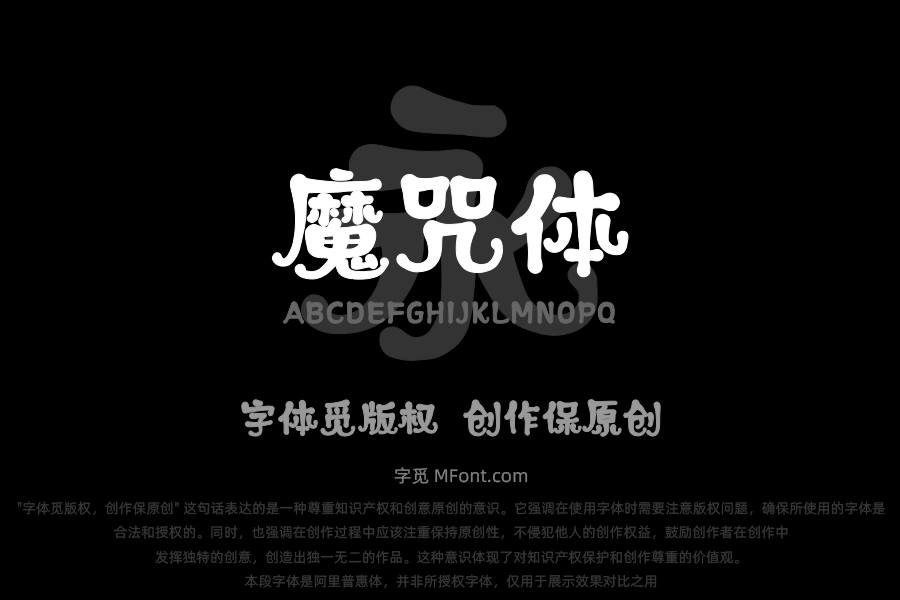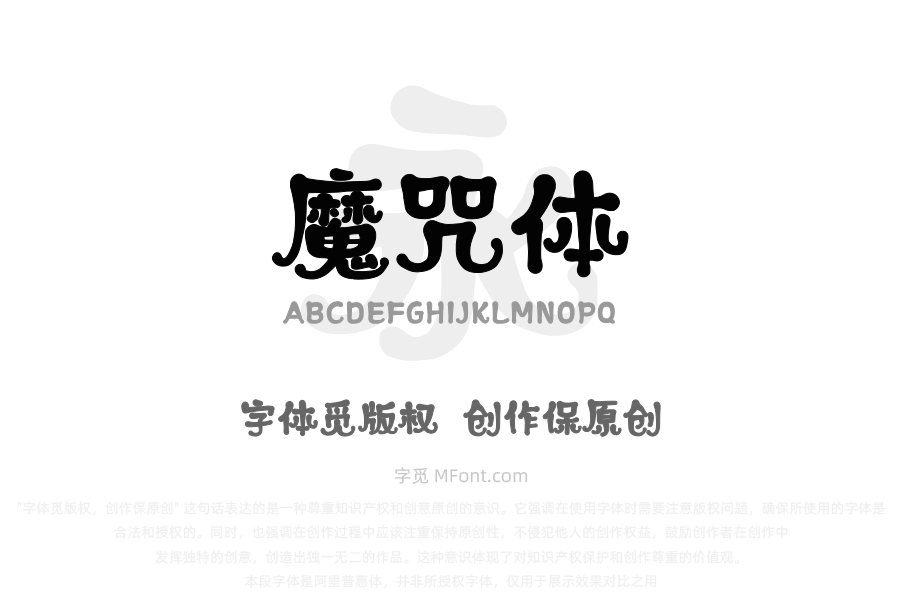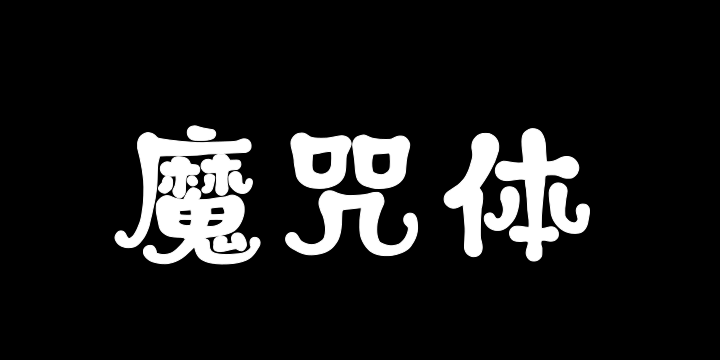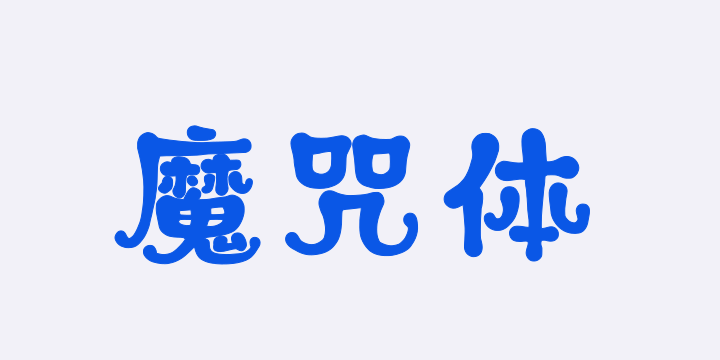
字体全名: 上首魔咒体
字体简介: 上首魔咒体,简体中文约6763字。这套字体在字形设计上,对传统汉字的结构进行了富有创意的变形与重塑,每个字都仿佛被赋予了 “魔咒” 般的独特气场,既保留汉字基本辨识度,又营造出奇幻、神秘的视觉效果,试图打破常规字体的平淡,为文字增添别样的表现力与想象空间,让观者在认读文字时,能感受到一种跨越寻常的独特韵味与神秘张力。
所属分类: 卡通手写体